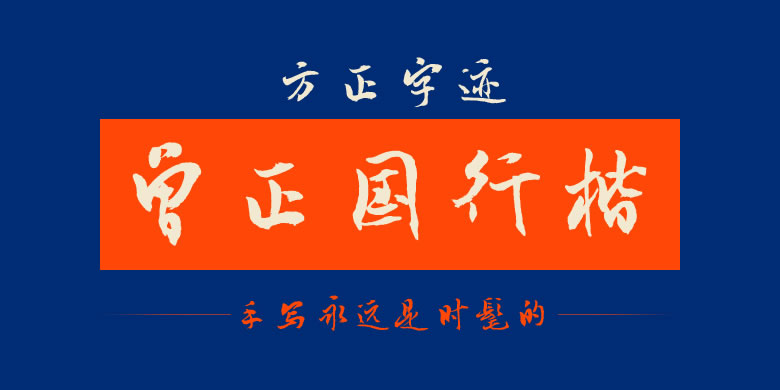
由现任中国书法家协会创作委员、文化部侨联文华阁书画院副院长的曾正国先生创作。曾正国,字庆予,号旁观者、澈心堂主人。曾获第一届全国书法“兰亭奖”第一名、第四届“赛克勒杯”国际书法赛佳作奖、第四届全国电视书法大赛三等奖等荣誉。其书法作品常被各类报刊登载或艺术团体收藏,《中国艺术报》、《中国书画报》、《大众生活报》、《新华网》等众多媒体曾作专题报道。方正曾正国行楷体巧妙的将行书的洒脱与楷书的规范相结合,字体飘逸流畅、书法意味浓,同时又不失端正、规范,做到了艺术性和实用性的统一。